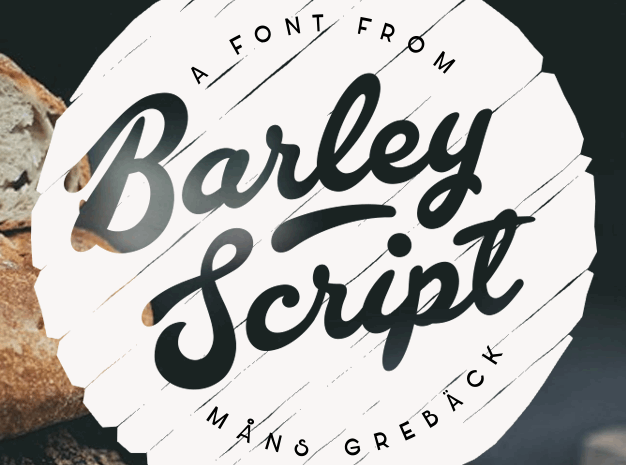
Barley Script Font – Download Grátis
A fonte ‘Barley Script Font’ é uma delicada e elegante maneira de adicionar um toque artesanal a qualquer projeto visual. Desenvolvida pelo designer sueco Måns Grebäck, essa fonte script oferece uma textura única que vai da suavidade ao detalhe meticuloso. O título ‘Barley’ é fácil e intuitivo, fazendo referência à própria fonte. Seu uso permite criar linhas de texto com sublinhados únicos ou até mesmo esticar essas linhas para criar uma linha mais comprida. Este recurso adicional oferece um grau maior de flexibilidade na criação de qualquer design. Para usuários que precisam de mais opções, a Fonte Barley Script é uma escolha ótima. Suportando ligaturas, permite uma linguagem fluida e natural à medida que o texto se mistura. Essa característica torna a fonte especialmente atraente para designers gráficos, principalmente aqueles criando materiais de propaganda ou marketing onde um ar de sofisticação é desejado. Agora que você entende melhor sobre essa fonte, pode personalizá-la em projetos e trabalhos de arte digitais. Sem dúvida, ela se encaixa perfeitamente no estilo da sua marca. Não hesite em visitar o site www.mn.sg/barley para adquirir a licença comercial desta linda fonte script.
Designer: Måns Grebäck